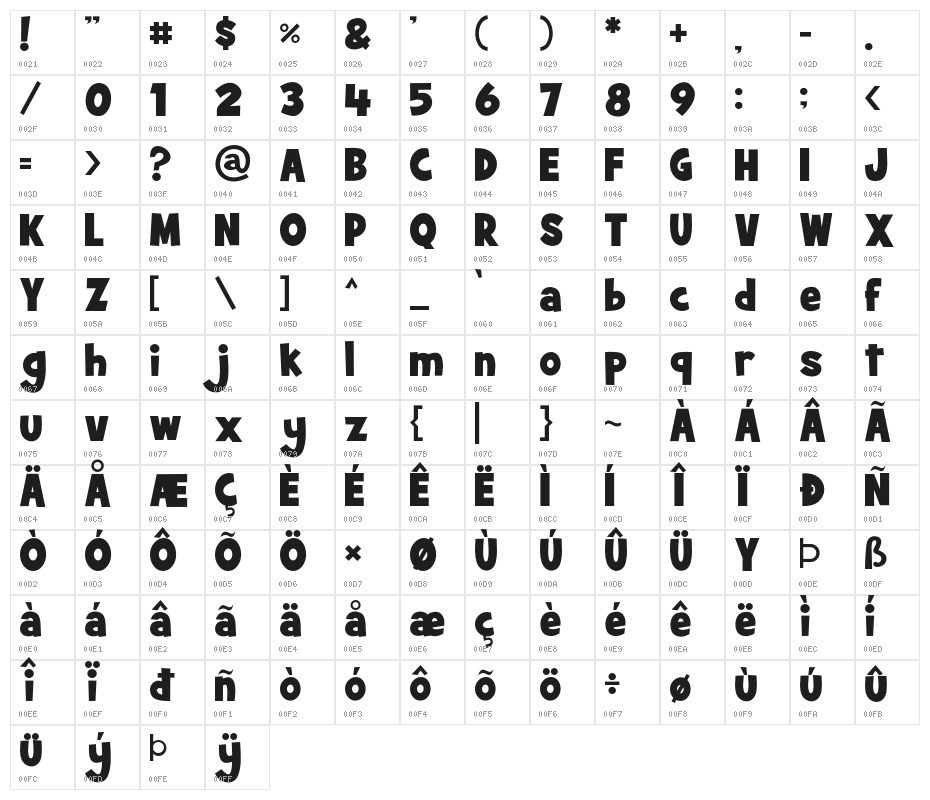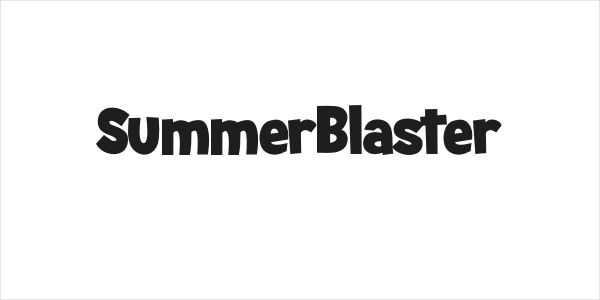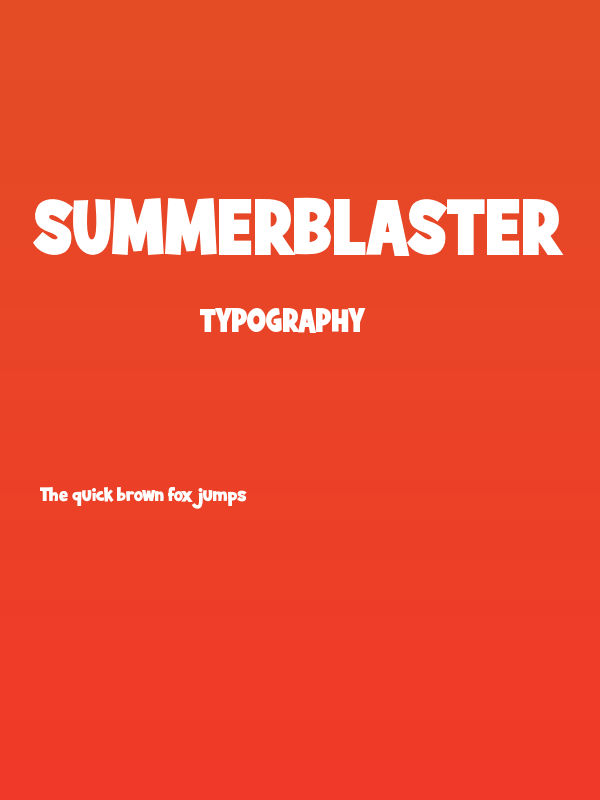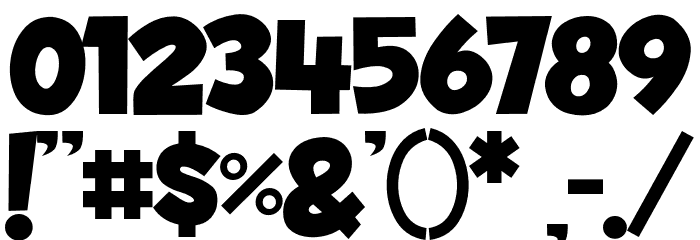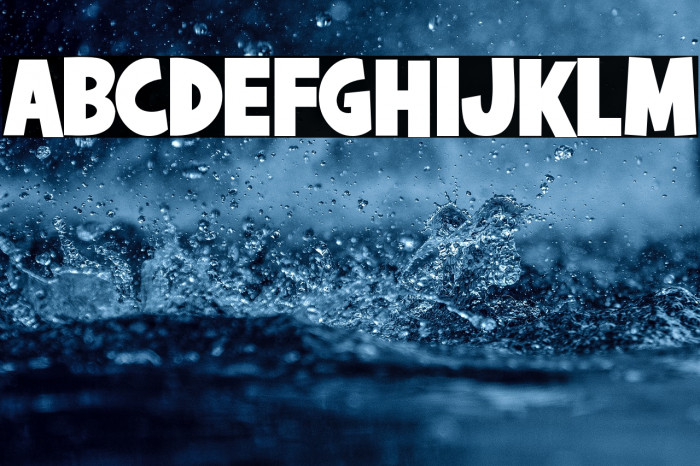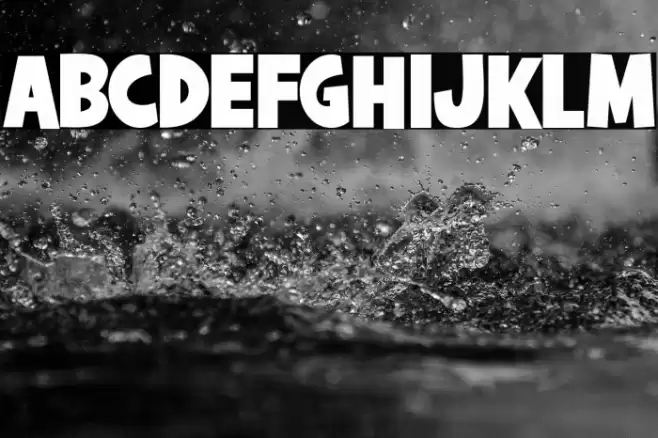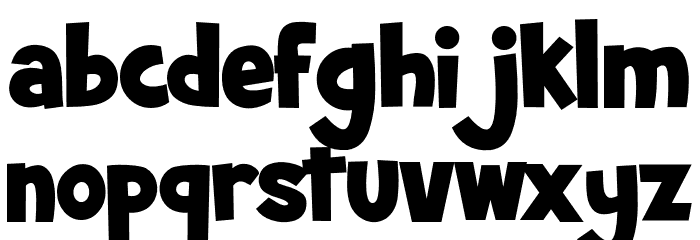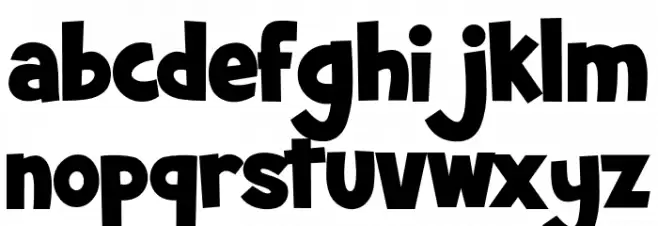
SummerBlaster Font
| Nume | SummerBlaster |
| Familia fontului | Summer Blaster |
| Proiecte propuse | Ideal for children's book covers, playful branding, party invitations, and eye-catching posters. |